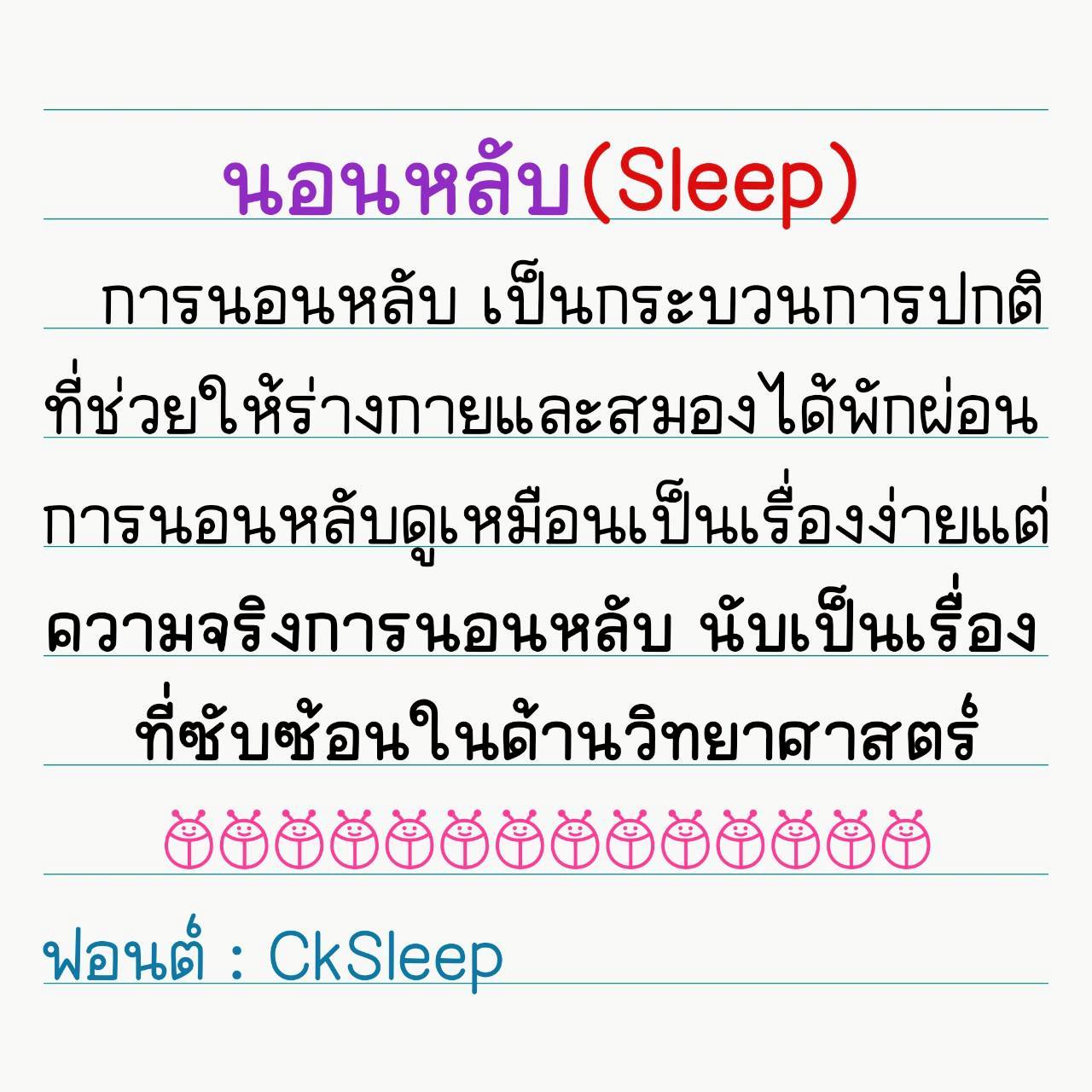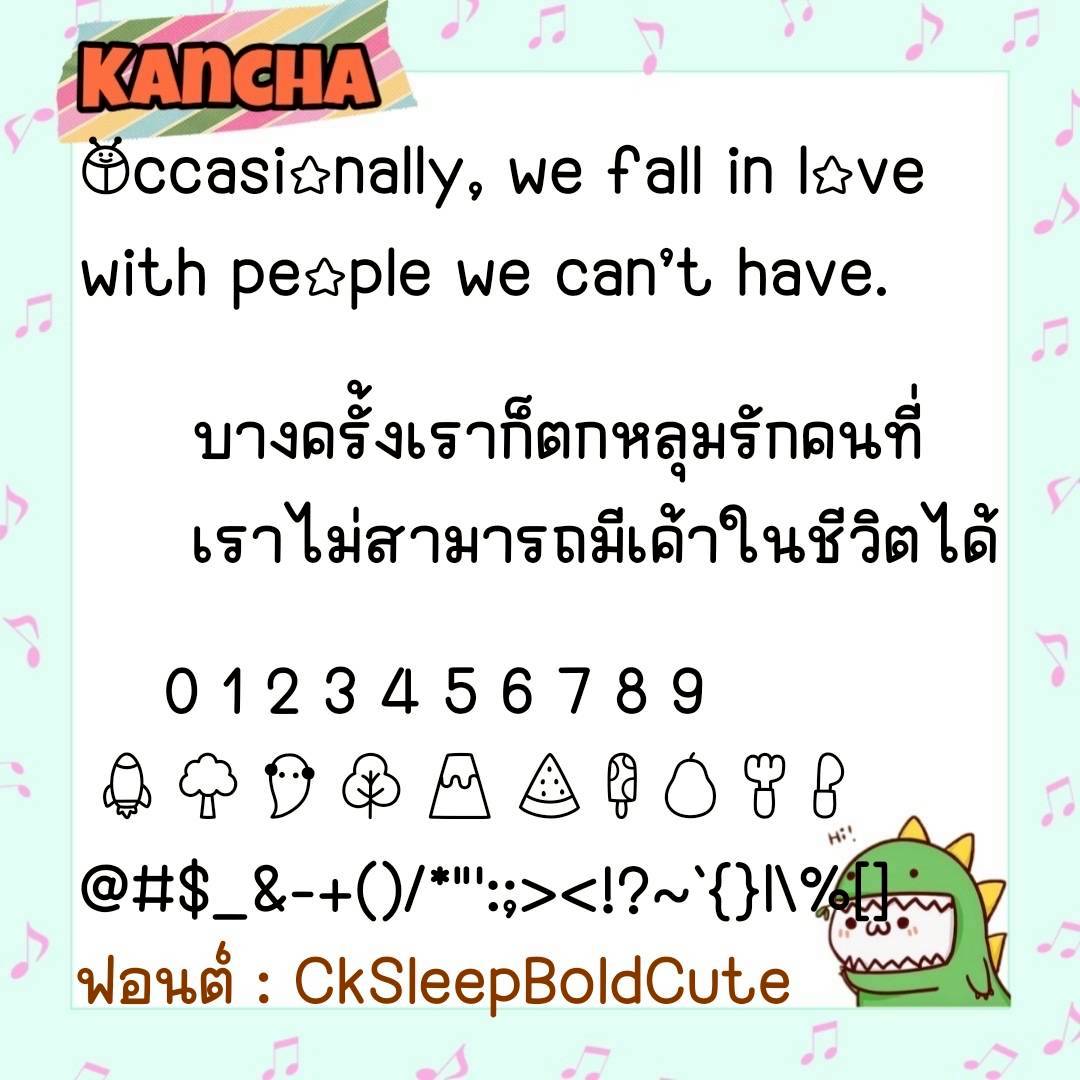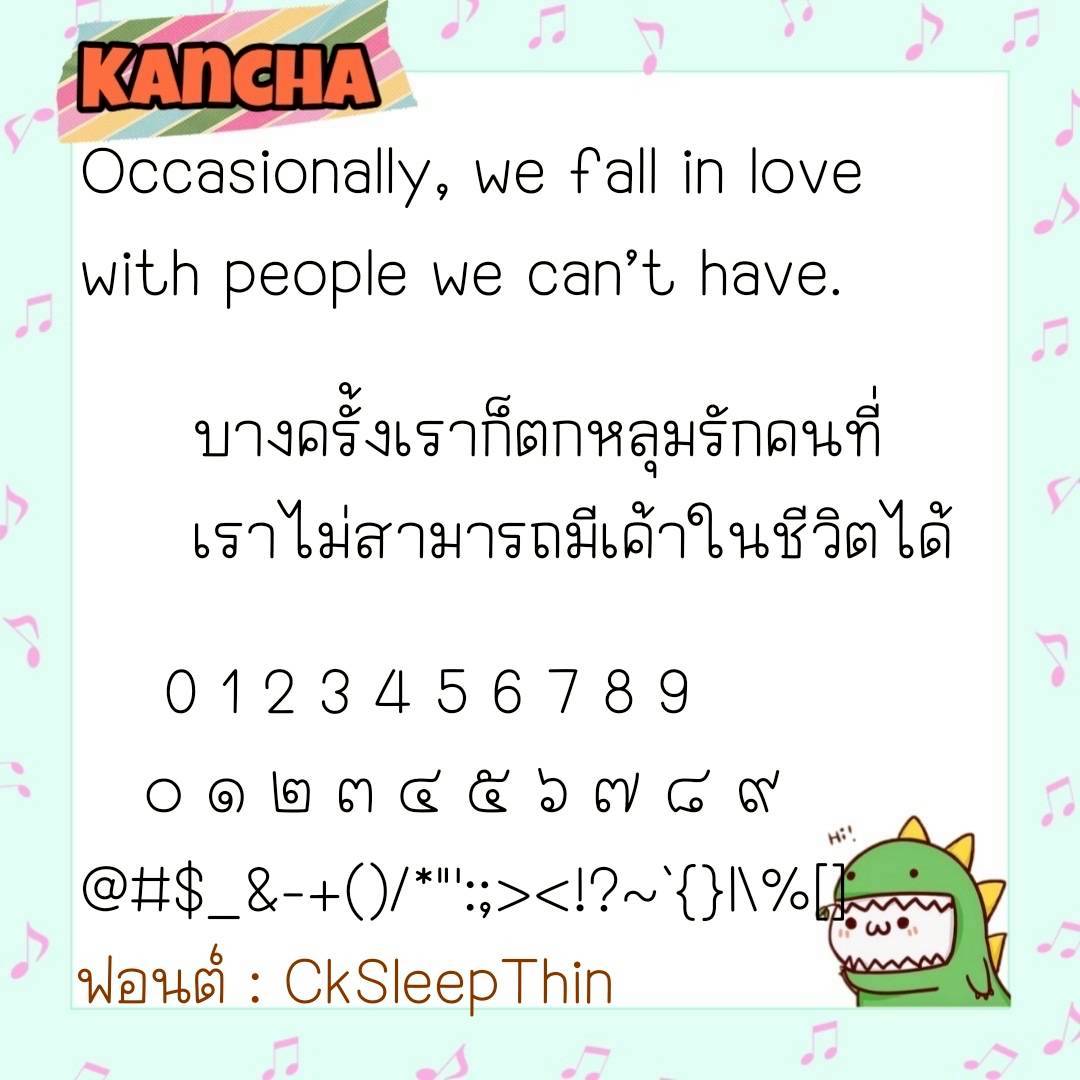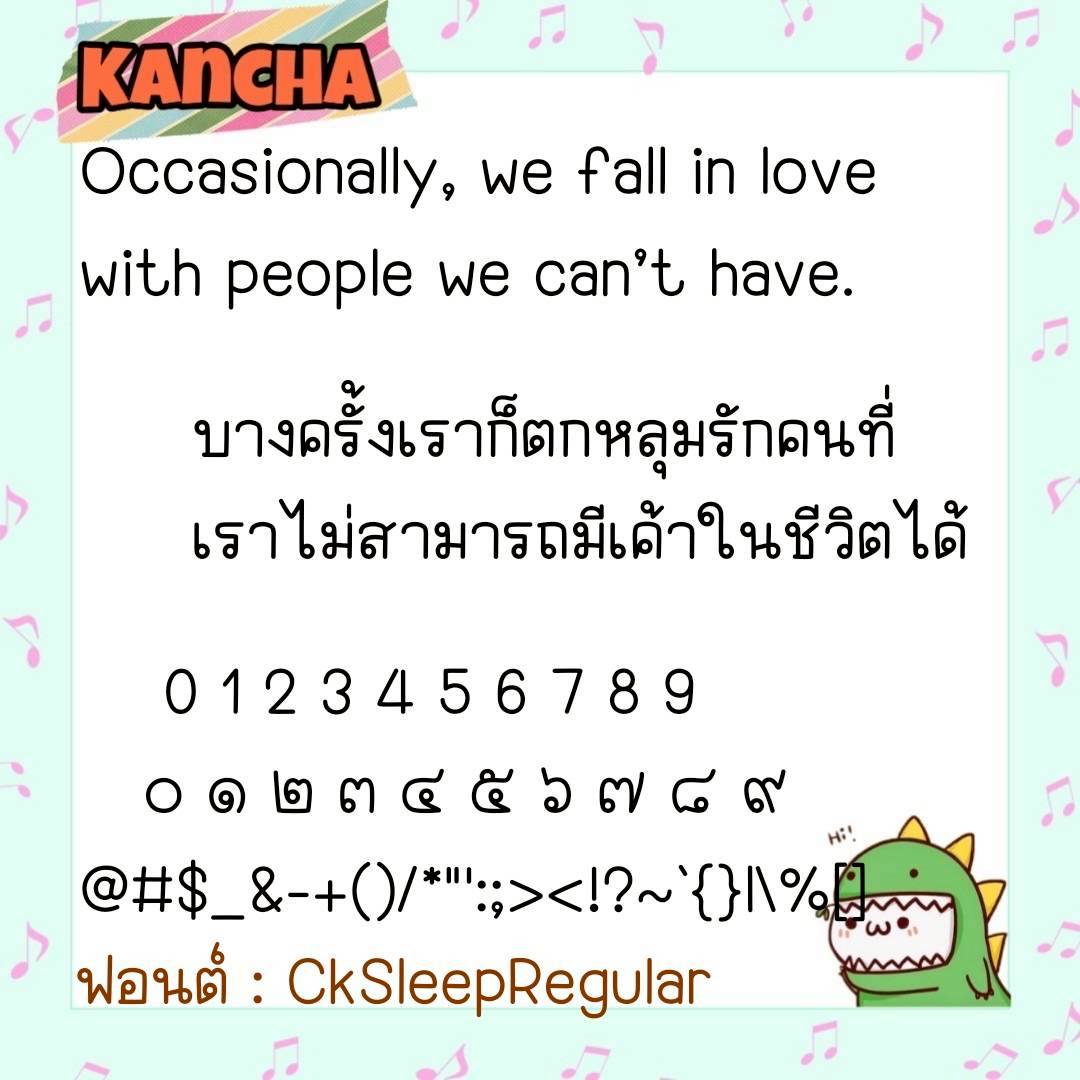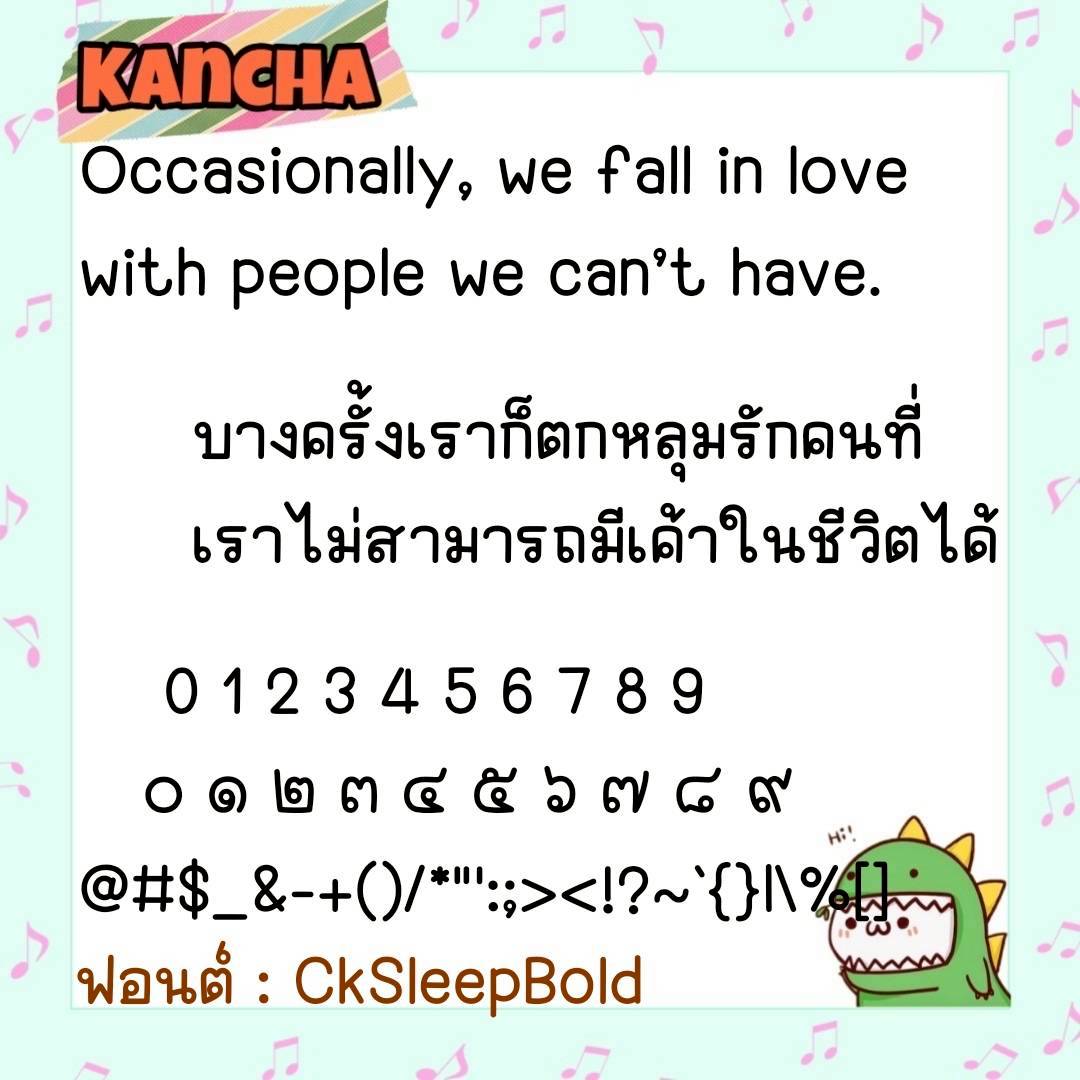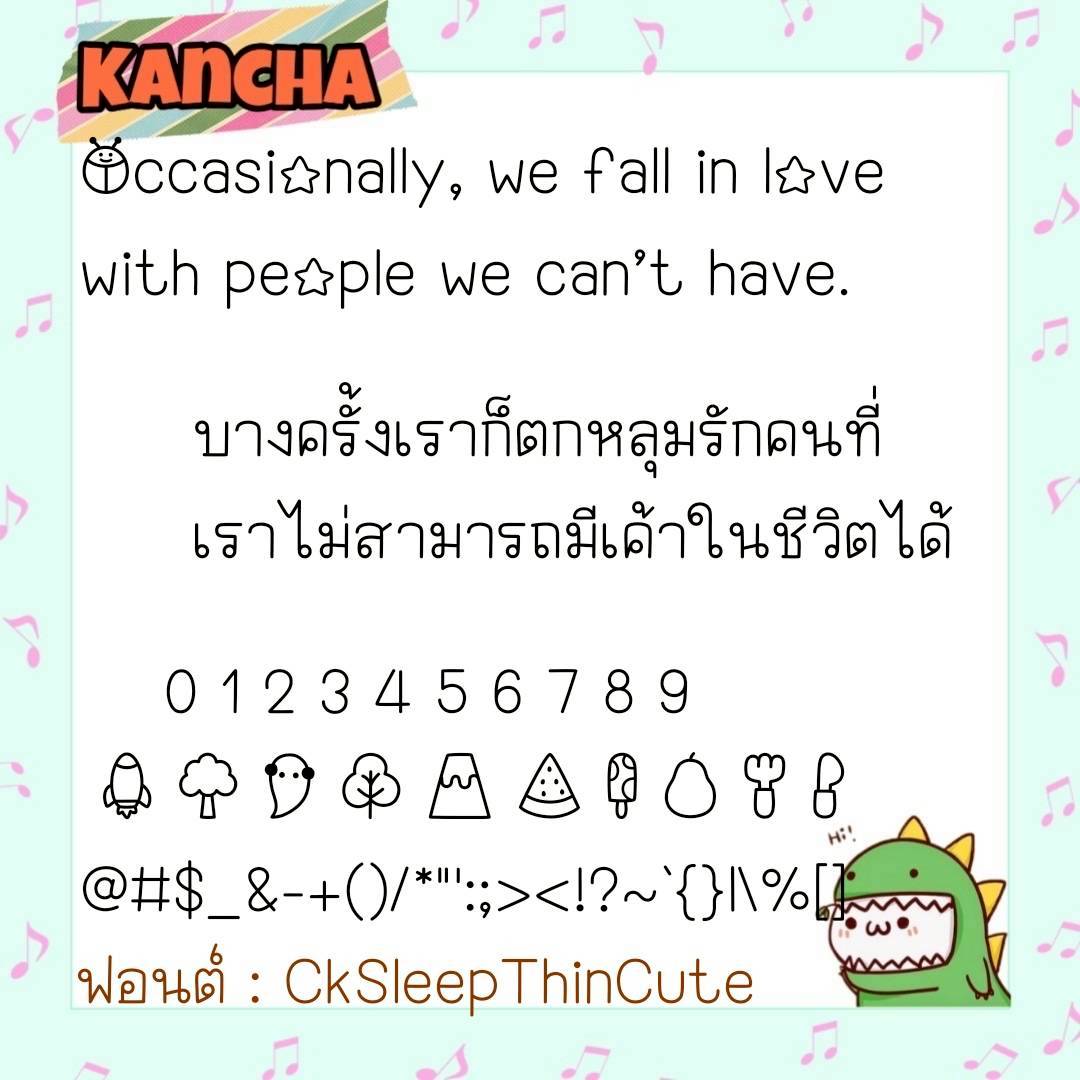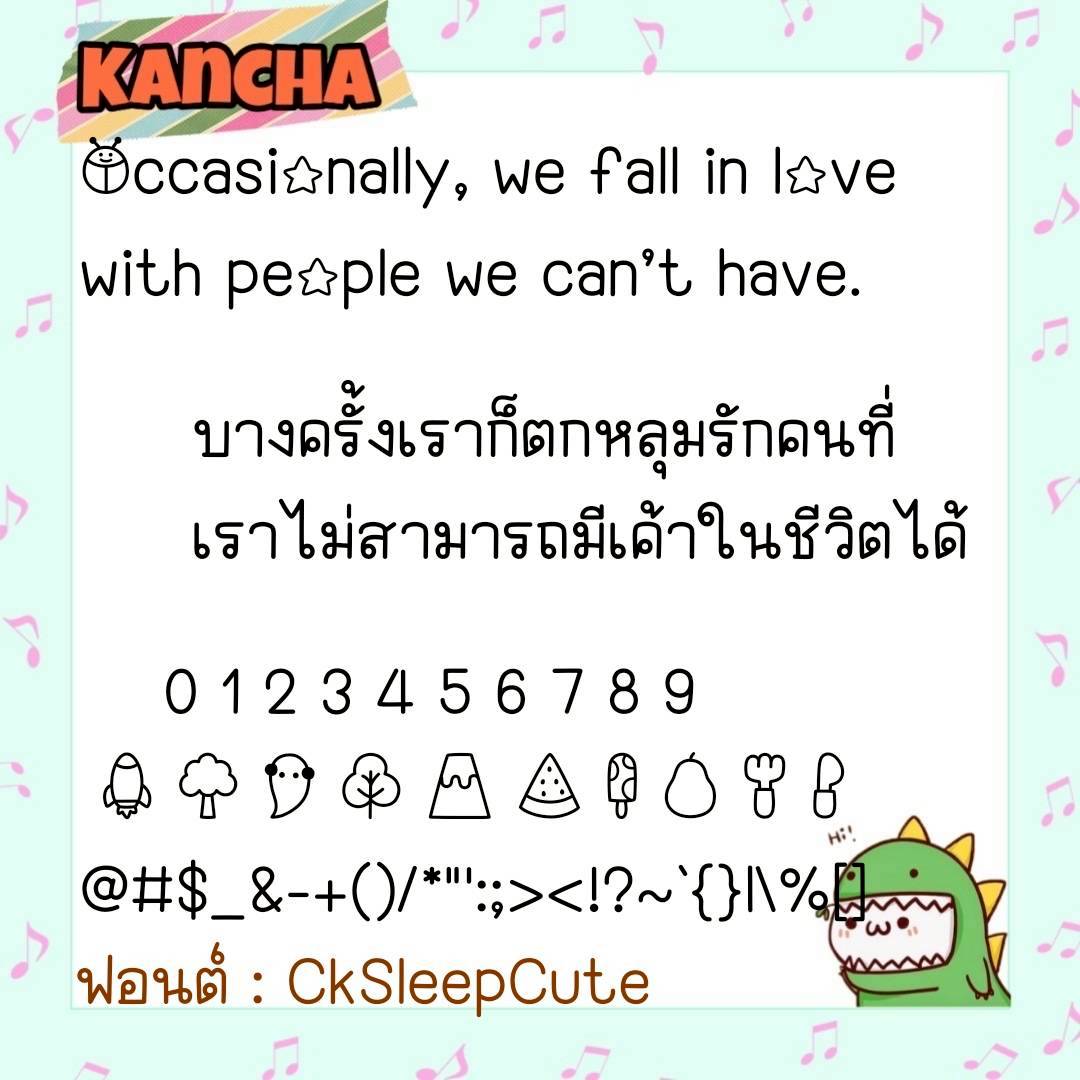
Font CkSleep
ชื่อสินค้า : Font CkSleep 💙
🔸 ฟอนต์ลายมือแนวเรียบร้อย ตัวฟอนต์กึ่งเหลี่ยมมีความเป็นระเบียบ เน้นอ่านง่ายสบายตา และยังมีไฟล์อิโมจิน่ารักๆที่ใช้แทนเลขไทยให้ด้วยค่ะ 🥰💙
🔹 This is a neat, handwritten font with a semi-square design, emphasizing readability and visual comfort. It also includes cute emoji files that can be used to replace Thai numerals. 🥰💙
🔸ฟอนต์ลายมือแนววัยรุ่น มีความยึกยัก น่ารักมีสไตล์ดูมีลูกเล่น ดูไม่น่าเบื่อ และยังมีไฟล์อิโมจิน่ารักๆที่ใช้แทนเลขไทยให้ด้วยค่ะฟอนต์ปรับสระเรียบร้อยไม่ลอย ไม่เหลี่ยม ใช้งานได้กับทุกโปรแกรม ได้ทั้ง ios(รองรับกับแอพต่างๆที่รองรับฟอนต์ในios เช่น Goodnote, Procreate)/android/คอมฯ/Ps/Word,Excel ได้หมดจ้าาาาา❤️❤️❤️